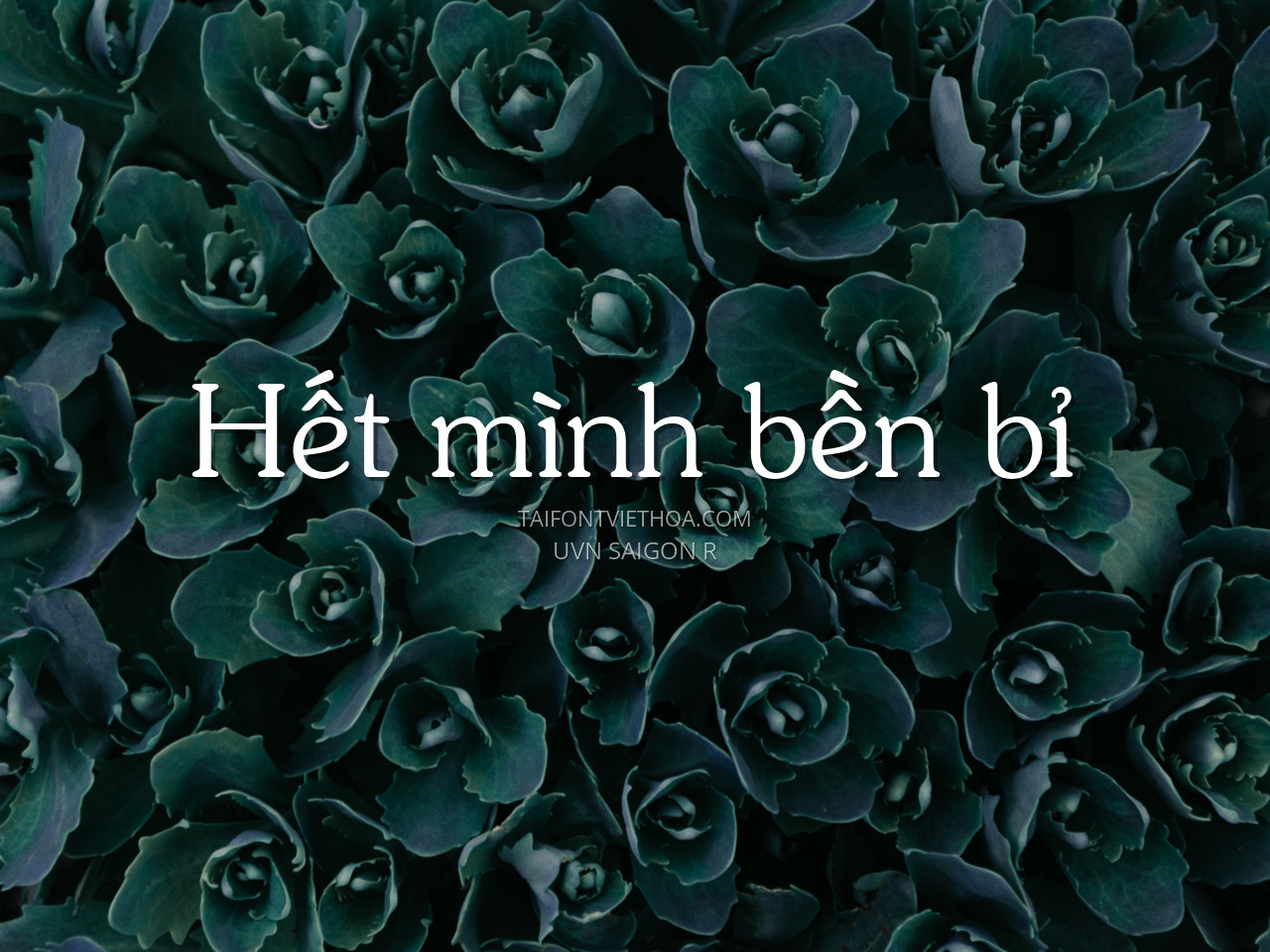
Font việt hóa UVN Sai Gon
Giới thiệu về font UVN Sai Gon
UVN Sai Gon là một font chữ mang đậm tinh thần hoài cổ và gợi nhớ về Sài Gòn xưa – một thành phố hoa lệ với những bảng hiệu retro, phông chữ kiểu biển tiệm vàng, tiệm sách những năm 60–80. Font được thiết kế với mục tiêu khơi gợi ký ức về một đô thị vừa hiện đại vừa lưu giữ dấu ấn thời gian. UVN Sai Gon được sưu tầm và chia sẻ bởi thành viên Font Chuẩn, và được taifontviethoa.com tuyển chọn kỹ lưỡng nhằm phục vụ những dự án thiết kế mang đậm bản sắc đô thị cổ, văn hóa miền Nam và ký ức thị thành.
Đặc điểm thiết kế và ứng dụng của UVN Sai Gon
Font UVN Sai Gon mang phong cách serif đậm chất retro, với các nét chữ vuông vức, gãy gọn nhưng vẫn mềm mại ở các đường cong chuyển tiếp. Kiểu dáng chữ mang hơi thở của biển hiệu tiệm xưa, bảng hiệu báo chí và sách vở Sài Gòn thập niên cũ. Font có độ dày vừa phải, dễ nhìn, hỗ trợ đầy đủ tiếng Việt, rất phù hợp để tạo dấu ấn thị giác trong các dự án có yếu tố hoài cổ, quảng bá địa phương hoặc thiết kế văn hóa vùng miền.
Ứng dụng lý tưởng: thiết kế poster retro, branding quán cà phê, bìa sách lịch sử, giao diện du lịch địa phương, bao bì sản phẩm thủ công. Ngành nghề phù hợp: ẩm thực truyền thống, quà lưu niệm, thiết kế văn hóa, du lịch, và ngành quảng cáo bản sắc địa phương.